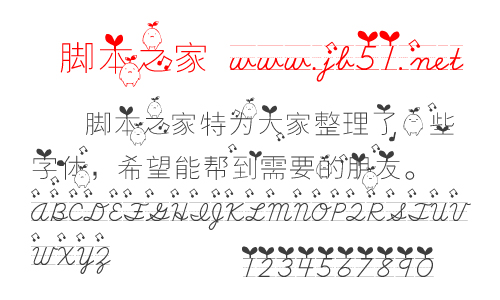
綠淺青燈體是一款非常優(yōu)秀好用的動(dòng)感設(shè)計(jì)方面的中文特色字體。綠淺青燈體字體每一個(gè)字都帶有音樂圖案,字形大方得體,整體效果十分出眾。字體可廣泛用于平面設(shè)計(jì),廣告設(shè)計(jì),報(bào)紙雜志,文本標(biāo)題等領(lǐng)域。歡迎大家前來下載使用。